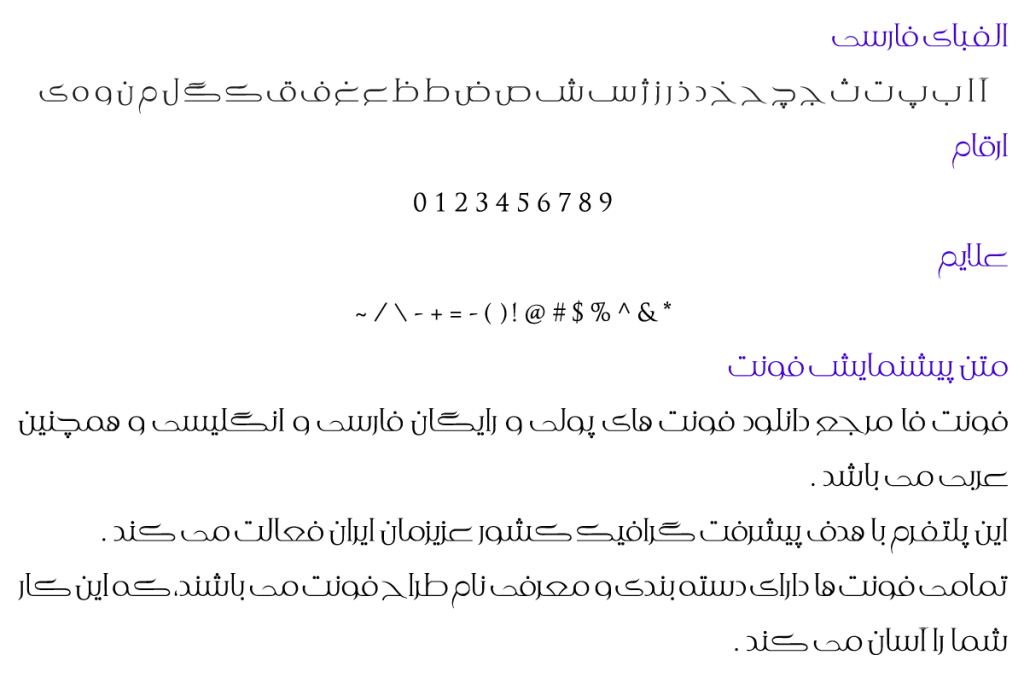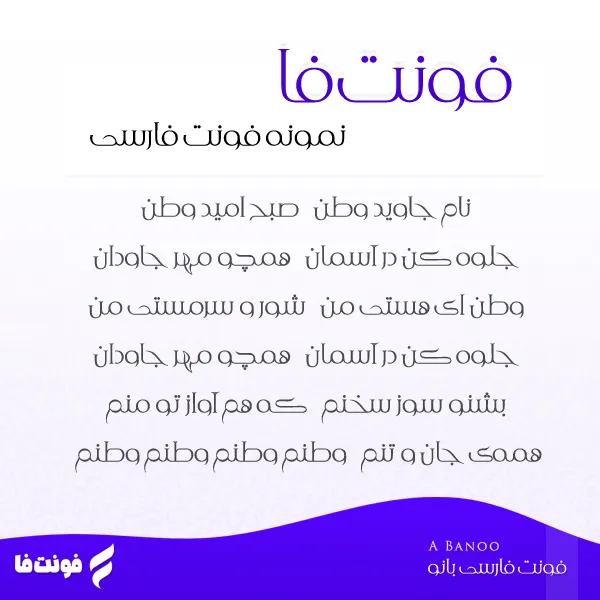
فونت فارسی بانو – A Banoo
توضیحات و معرفی فونت بانو
فونت فارسی بانو ( A Banoo ) از مجموعه فونت های آزاد می باشد، و نیز نوع فونت فانتزی می باشد.
این تایپ فیس در اصل یک فونت عربی بوده که توسط یک گرافیست عرب زبان طراحی شده است.
این فونت بعدها توسط مجموعه ایران فونت بومی سازی و به زبان فارسی تبدیل شده و اعداد و حروف فارسی به آن افزوده شده اند.
و نیز فونت A Banoo در یک وزن معمولی است.
در تصویر زیر میتوانید شعر دلنشین «نام جاوید وطن» را ببینید که با این تایپ فیس فارسی طراحی شده است.